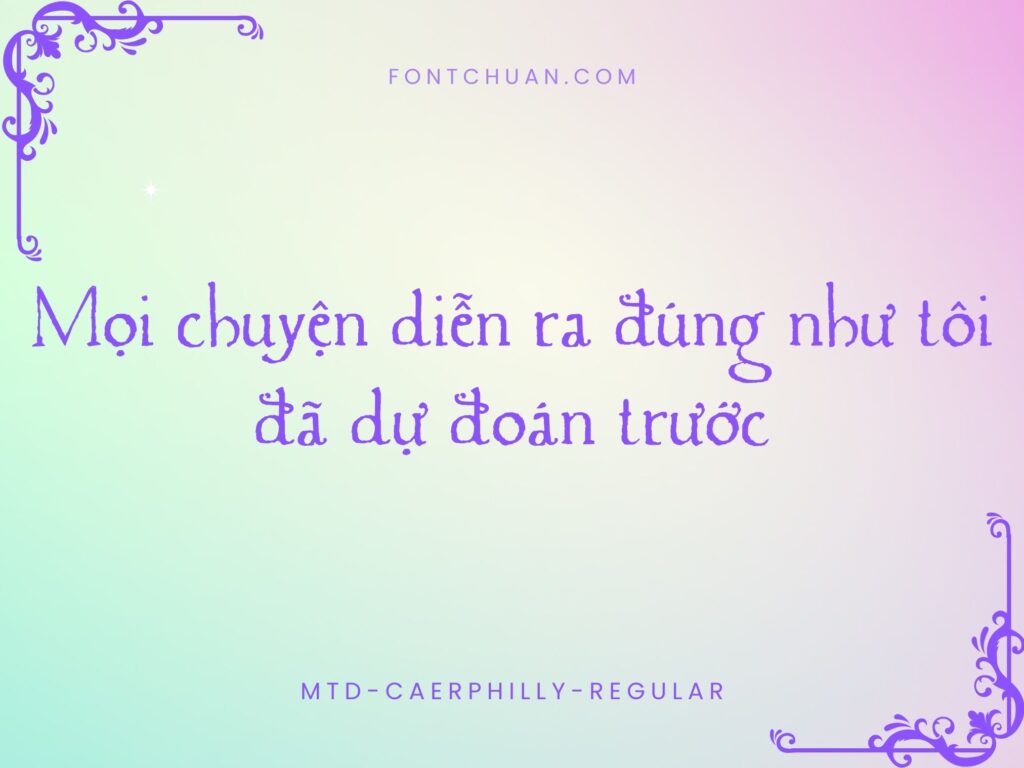
Font MTD Caerphilly Regular Việt Hóa
Font MTD Caerphilly Regular là một kiểu chữ viết tay mang phong cách cổ điển, được thiết kế với các đường nét mềm mại và uyển chuyển. Font này hỗ trợ đầy đủ tiếng Việt cùng hơn 90 ngôn ngữ khác, mở rộng khả năng ứng dụng trong các thiết kế đa ngôn ngữ. Đây là một trong những phông chữ được cộng đồng thiết kế đánh giá cao và sử dụng trong nhiều dự án sáng tạo, đáp ứng nhu cầu đa dạng của người dùng.
MTD Caerphilly Regular nổi bật với vẻ đẹp thanh lịch và cổ điển, tạo cảm giác thân thiện và gần gũi. Font rất phù hợp cho các thiết kế logo, tiêu đề, bao bì sản phẩm, thiệp mời và các ấn phẩm đòi hỏi sự tinh tế và nghệ thuật. Các ngành nghề phù hợp bao gồm quảng cáo, giáo dục, công nghệ, thiệp cưới và ảnh cưới. Font này cũng lý tưởng cho các sự kiện như Tết, Giáng sinh, Valentine và các lễ hội khác.